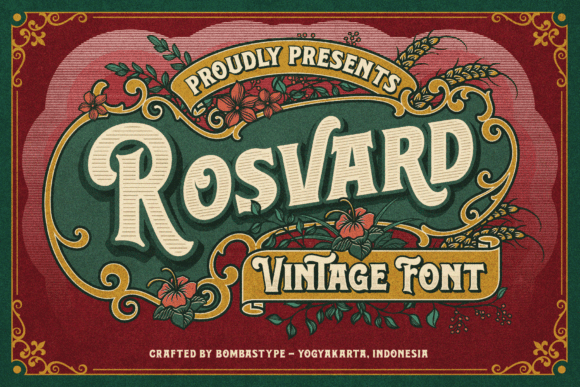
Название: Rosvard Font
Rosvard - это смелый и выразительный шрифт, выполненный в винтажном стиле.
Добавьте этот шрифт с толстыми буквами в свои проекты и заметите, как он выделяет ваши творения.
Название: Rosvard Font
Rosvard - это смелый и выразительный шрифт, выполненный в винтажном стиле.
Добавьте этот шрифт с толстыми буквами в свои проекты и заметите, как он выделяет ваши творения.